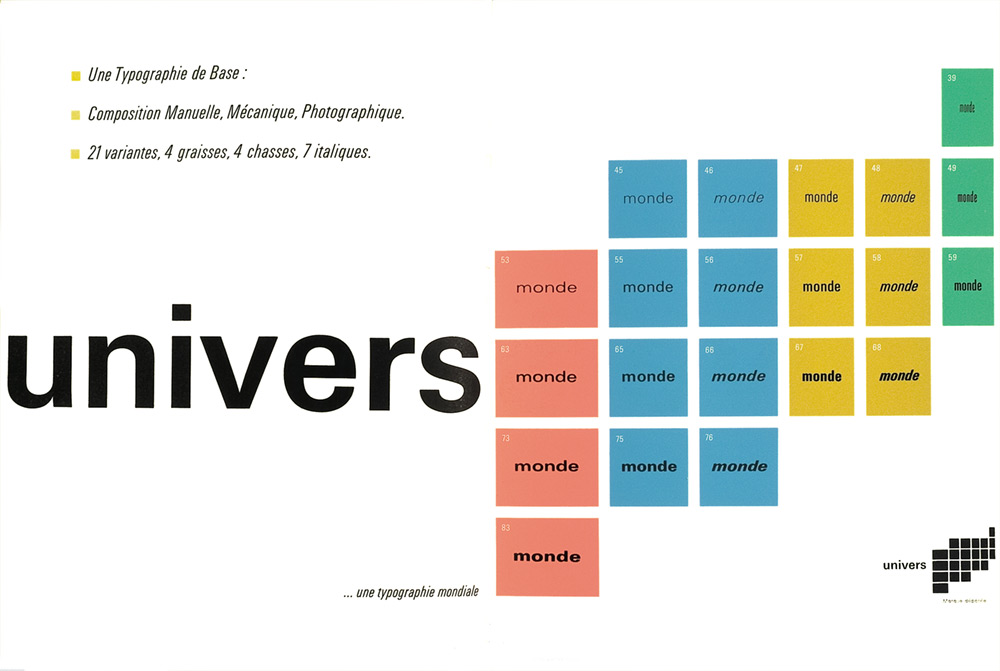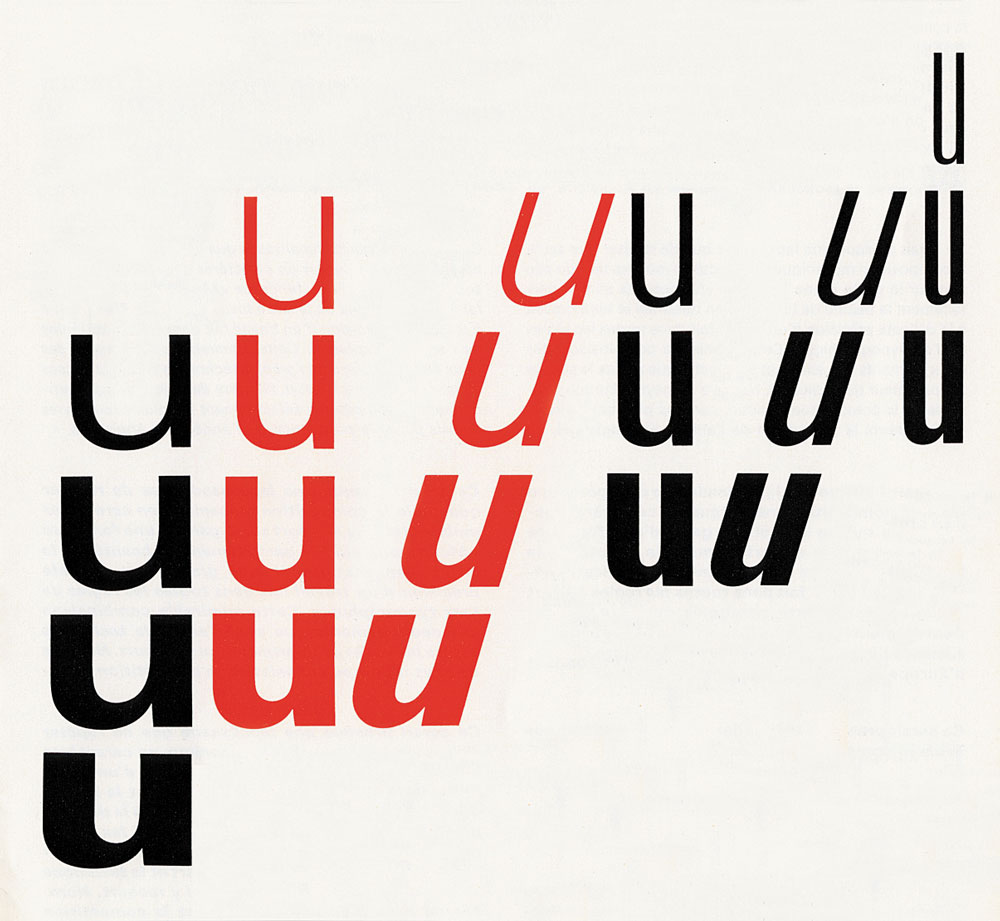
Joyeux anniversaire Adrien Frutiger
Voici deux pages du catalogue «specimen» de la fonderie Deberny et Peignot, consacrées au lancement de cette série mythique d’Univers qui fut sans doute une des premières production «marketing» dans le monde de la composition dite froide (photocomposition). Cette série fut mise au point sous la direction d’Adrien Frutiger par deux typographes émérites: Albert Boton et Ladislas Mandel. Ils ont été le fleuron des caractères Lumitype et ont remporté un succès à la fois commercial et d’estime dans toute profession des Arts Graphiques. (Avec mes remerciements à Michel Wlassikoff qui a eu la gentillesse de me passer ces documents).
Juste quelques souvenirs personnels. J’ai eu l’occasion de rencontrer Adrien à de nombreuses occasions, puisque aussi bien à Lure dans le cadre des Rencontres Internationales de Lurs en Provence qu’à son bureau de la rue Cabanis chez Deberny et Peignot du temps où Charles Peignot présidait encore cette société malheureuse, qui n’a pas eu les moyens de développer la première photocomposeuse (Lumitype) inventé par deux ingénieurs Français, Higonnet et Moiroud. Je l’ai rencontré aussi assez souvent dans les assemblées générales de l’ATYPI, à Paris, Berlin, Bâle, Oxford, Hambourg.
Indirectement aussi, parce que Ladislas Mandel disparu depuis peu était un ami de la famille et qu’il dirigeait l’atelier de réalisation de Deberny et Peignot… que Ladislas nous a parlé longuement des méthodes et théories de la lisibilité chères à A. Frutiger.
J’ai même une anecdote cocasse: un jour, en 1993, j’ouvre une des polices, l’AVENIR dessiné par Adrien pour Linotype. Et o surprise, l’italique était en en réalité un romain penché. Déformé électroniquement. J’appelle aussitôt Adrien dans son atelier, et il me répond très gentiment que «oui, Linotype voulait qu’il dessine la série des italiques de cette police». Chose qu’Adrien pour des raisons paléontologiques se refusait. Une chose est le marketing dans l’industrie de la typo, une autre les racines culturelles qui normalement devraient nous interdire de dessiner une linéale (type Europe, Futura) en italique. C’est assez contraire à l’origine des tracés des phéniciens. Mais commerce oblige, Adrien, me dit-il, avait donné l’autorisation à Linotype de déformer son caractère afin de proposer une famille complète, toutes les graisses, en romain et italique.
Je crois que par la suite cette erreur avait été corrigée, et que soit Adrien lui même, soit le bureau de dessin de la firme allemande sous le contrôle du Maître, ont fini par produire un dessin tout à fait honorable de l’AVENIR en ital.
Voilà, que dire, sinon vous renvoyer sur tous les sites qui relatent la vie, et l’immense œuvre de ce typographe suisse qui ne s’est jamais départi de sa gentillesse, de son goût pour les formes bien construites. Une sorte de Jean Sébastien Bach de la typographie bien tempérée qui n’a jamais oublié que la première fonction d’une typo est de véhiculer un message, un texte. Le plus lisiblement, de loin (typos pour les aéroports de Montréal) comme de près. Son Frutiger restera une des linéales les plus alternatives lorsque vous hésitez entre un Futura, trop géométrique, ou un Helvetica trop neutre, ou encore un MetaPlus, presque trop moderne. Son travail sur le caractère Frutiger s’apparente à celui d’un Eric Gill, qui sut allier tracé originel, et construction rigoureuse.